Font merupakan jenis-jenis gaya huruf, yang mana ini merupakan salah satu elemen penting dalam desain grafis. Tulisan akan menjadi lebih menarik jika menggunakan jenis atau gaya font yang sesuai. Penting untuk dipahami jika terdapat beberapa cara untuk mengkombinasikan font dalam desain grafis agar menarik.
Tipografi dalam desain grafis memiliki peran penting untuk menyampaikan pesan dengan efektif. Untuk itu penting memilih jenis font yang tepat agar mudah untuk dibaca sehingga efektif untuk menyampaikan informasi dan pesan. Terkadang untuk membuat tampilan desain lebih bisa menggunakan lebih dari satu jenis font.
Untuk bisa mengkombinasikan font dalam satu desain penting untuk memilih jenis font yang cocok satu sama lain. Hal ini agar tampilan desain seimbang dan terlihat lebih menarik. Simak artikel ini, untuk memahami cara mengkombinasikan font dalam desain grafis.
CARA MENGKOMBINASIKAN FONT DALAM DESAIN GRAFIS
Dalam mengatur jenis font dalam desain grafis, penting untuk memerhatikan bahwa jenis font menarik, mudah dibaca dan bisa menyampaikan pesan dengan efektif. Berikut beberapa cara mengkombinasikan font dalam desain:
Pilih Font yang Terlihat Melengkapi
Untuk menciptakan kombinasi font yang menarik, penting untuk memilih font yang saling melengkapi satu sama lain. Kombinasi jenis font yang terlihat saling melengkapi, font yang memiliki suasana yang sama akan cocok jika dipadukan. Pertimbangkan untuk memilih font yang memiliki style berbeda namun terlihat menyatu dengan baik.
Font yang terlihat melengkapi biasanya dari famili font yang sama, sehingga gayanya tidak jauh berbeda. Hati-hati bila ingin mengkombinasikan font dari jenis style berbeda, pastikan ketika disatukan terlihat menarik dan menciptakan harmoni.
Kombinasi Serif dan San serif
Untuk yang menggunakan font serif, gunakan kombinasi font dengan sans serif akan terlihat bekerja dengan baik. Kombinasi dua font yang masih satu famili ini biasanya akan berhasil dan membuat tampilan tulisan nyaman untuk dibaca. Kedua font ini cukup sederhana sehingga mudah untuk dibaca ketika diterapkan pada desain grafis.
Serif dan sans-serif ini kerap kali digunakan karena memudahkan keterbacaan pesan, bentuk font yang sederhana juga memudahkan untuk terlihat cocok dengan elemen atau tema desain. Font serif yang memiliki ciri terdapat ekor atau garis kecil pada setiap sudutnya ini akan cocok jika dikombinasikan sans serif yang tidak memiliki ekor pada setiap ujungnya. Gunakan Serif sebagai judul dan sans serif sebagai jenis font deskripsi, ataupun sebaliknya juga akan tetap terlihat cocok.
Hindari Menggunakan Font yang Terlalu Mirip
Ketika ingin mengkombinasikan dua atau lebih jenis font yang berbeda, penting untuk menghindari jenis font yang sama. Font memiliki banyak sekali gaya dan jenis font yang bisa digunakan dalam desain, namun banyak juga font yang terlihat mirip. Untuk memastikan kombinasi font terlihat menarik pada tampilan desain grafis, gunakan jenis font yang berbeda.
Jika ingin menggunakan font yang mirip pastikan ketebalan atau ciri tertentu yang sedikit berbeda. Ketebalan dan jarak antar huruf dapat memengaruhi tampilan font. Pastikan untuk memilih jenis font berbeda agar tampilan tulisan pada desain lebih berdimensi.
Gunakan Kontras
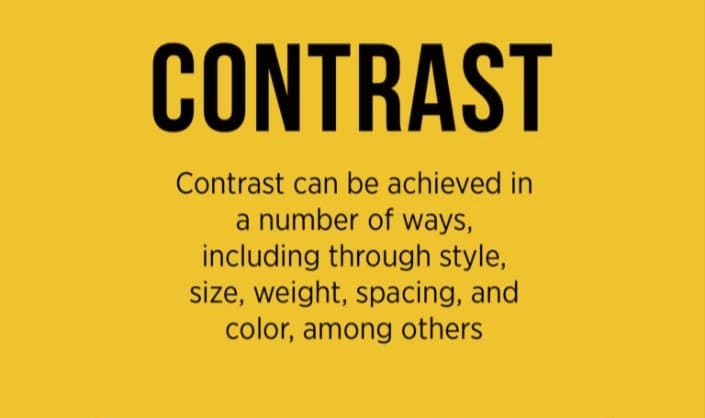
Dalam merancang desain grafis, tulisan dan jenis fontnya juga perlu memiliki kontras antar teks atau informasi. Terkadang dalam satu desain menggunakan beberapa teks, pastikan untuk menciptakan kontras pada tulisan yang utama. Kontras berguna untuk menyoroti teks utama yang membawa informasi penting seperti judul.
Kontras akan membuat tampilan desain lebih menarik, untuk menciptakan kontras pada teks gunakan gaya font yang berbeda. Selain jenis font yang berbeda, pastikan juga font memiliki ketebalan, ukuran dan warna yang berbeda. Penting juga mengatur spasi dan kerning agar teks bisa terlihat menonjol.
Gunakan Font dengan Terbatas
Dalam sebuah desain grafis terkadang menggunakan beberapa teks yang berisi informasi penting. Meskipun terdapat banyak tulisan, hindari penggunaan jenis font yang terlalu banyak. Fokuskan untuk menggunakan dua sampai tiga jenis font saja. Hal ini untuk menghindari Desain terlihat kacau dan tidak memiliki fokus utama.
Audiens bisa bingung ketika melihat ada terlalu banyak jenis font yang digunakan. Pastikan untuk menggunakan font yang terlihat cocok satu sama lain. Terlalu banyak jenis font dengan gaya cukup kontras dapat membuat desain grafis terlihat aneh dan terlalu ramai.
Gunakan Font dari Famili yang Sama
Untuk memastikan kombinasi font menciptakan suasana yang sama, gunakan font dari famili font yang sama. Dalam satu famili biasanya terdapat banyak sekali font yang bisa digunakan. Kombinasikan font dari famili yang sama untuk menciptakan harmoni dalam desain. Biasanya font dari famili yang sama akan memiliki ciri dan gaya yang mirip, ini bisa membantu menciptakan konsistensi.
Buatlah Kombinasi tetap Sederhana
Ketika akan mengkombinasikan font dalam satu desain, pastikan kombinasi dua font atau lebih yang dipilih memiliki kesatuan dan terlihat sederhana. Hindari memadukan font yang terlalu nyentrik dan unik, ini bisa menyulitkan pembacaan. Pastikan untuk memilih kombinasi font yang terlihat sederhana dan bekerja dengan baik satu sama lain.
Untuk menciptakan kombinasi font yang menarik dan terlihat sederhana, gunakan font dari famili font yang sama, misalnya font sesama serif. Kombinasi dari famili font yang sama akan terlihat sederhana, namun gunakan ketebalan yang berbeda agar terlihat menarik.
Kombinasikan Font dari Era yang Sama
Jenis font terkadang mencerminkan suatu era tertentu, untuk mengkombinasikan font dari era tertentu, pastikan memilih jenis font yang cocok. Kombinasikan font dari era yang sama namun terlihat berbeda agar menciptakan kesan yang unik. Desain grafis yang menggunakan kombinasi font dari era tertentu dapat digunakan untuk mencerminkan era tersebut.
Sesuaikan kombinasi font dari era yang sama dengan tema desain agar menciptakan konsistensi. Meskipun dari era yang sama pastikan font tidak terlalu mirip dan menciptakan dimensi yang unik ketika dikombinasikan.
Baca juga: 7 Situs yang Menyediakan Font Gratis untuk Desain
Pertimbangkan Tekstur dan Warna
Ketika mengkombinasikan font, perhatikan juga warna dan teksturnya, ada beberapa jenis font yang unik memiliki tekstur tertentu. Warna dalam tks berperan penting untuk memperindah tampilan font. Pilih warna yang berbeda pada jenis font yang berbeda, namun pastikan agar terlihat cocok dan menciptakan harmoni.
Untuk jenis font yang memiliki tekstur gunakan secara hati-hati agar tidak terlihat berlebihan. Gunakan warna untuk menyoroti teks utama, lakukan eksperimen dengan efek visual seperti bayangan aau outline pada font. Hal ini dapat membuat kombinasi font semakin menarik dan terlihat mencolok.
Dalam mengkombinasikan font dalam desain penting untuk memahami jenis-jenis font dan familinya, agar bisa mengkombinasikan font dengan tepat. Untuk bisa mengkombinasikan dua atau lebih font yang berbeda dalam desain grafis ada beberapa cara yang harus diperhatikan. Mengkombinasikan font tidak bisa dilakukan dengan sembarangan karena bisa memengaruhi tampilan desain dan keterbacaan teksnya.